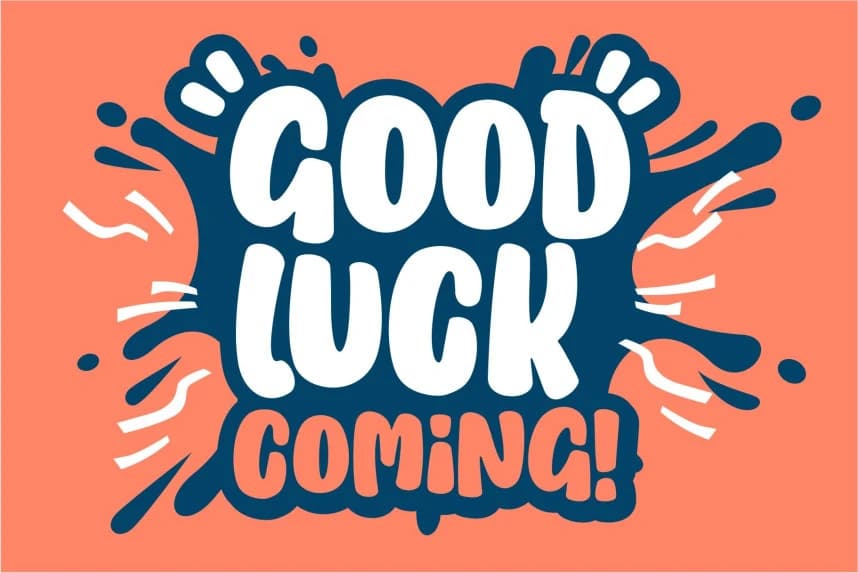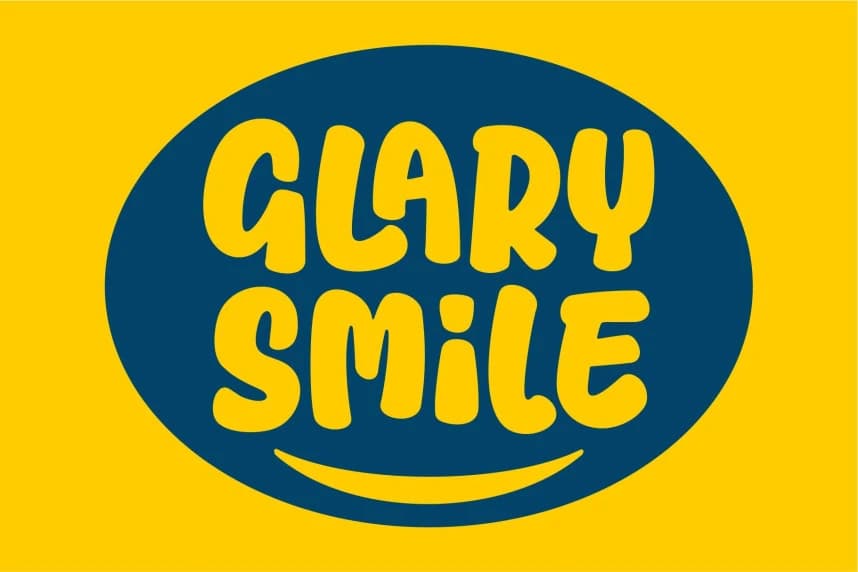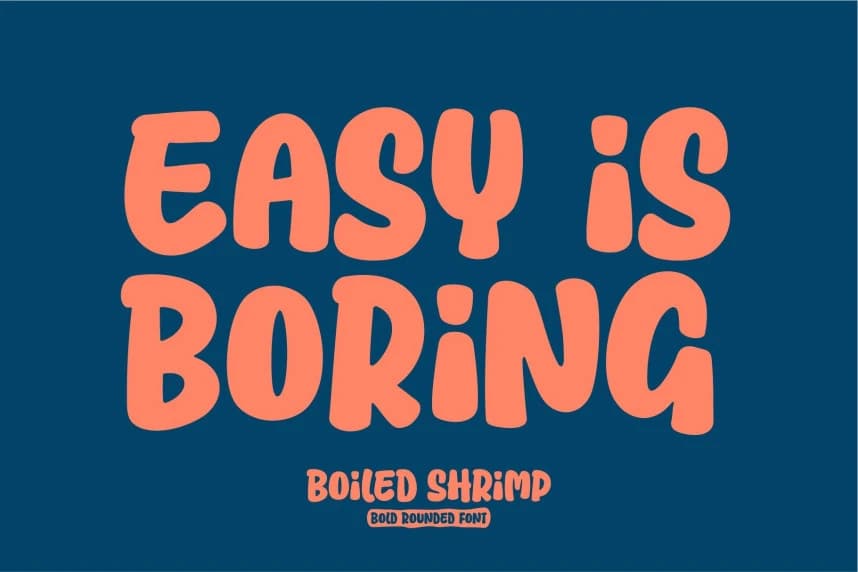
Boiled Shrimp Yazı Tipi
Boiled Shrimp Font! Bu, benzersiz karakterler için oluşturduğum el yazısı bir fonttur. Biraz yuvarlatılmış ve çok güzel. Büyük ve küçük harfler için Aa-Zz aralığındaki alternatif harfleri içerir. Logolar, alıntılar, sanat eserleri, tabelalar, başlıklar, ambalajlar, etiketler ve herhangi bir el yapım
Boiled Shrimp Font Bu, benzersiz karakterler için oluşturduğum bir el yazısı fontudur. Biraz yuvarlatılmış ve çok güzel. Üst ve alt harfler için Aa-Zz aralığındaki alternatif harfleri içerir. Logolar, alıntılar, sanat eserleri, tabelalar, başlıklar, ambalajlar, etiketler ve herhangi bir el yapımı dokunuşa uygun görünüyor.